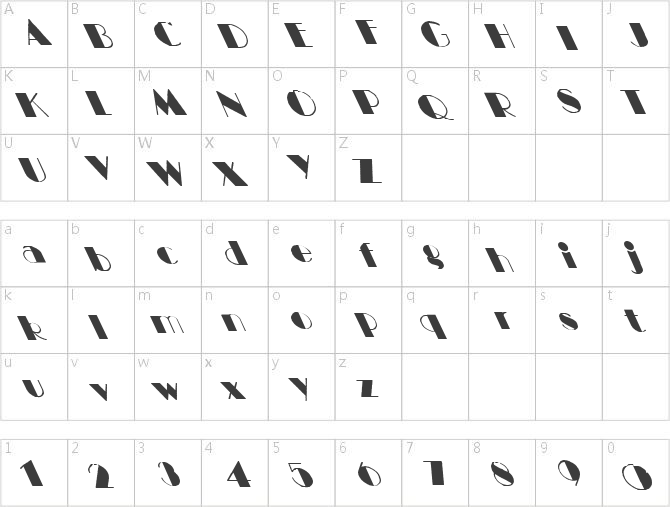
字体名称: BIGCITY
BIGCITY-Normal Extreme Lefty
BIGCITY-Normal Extreme Lefty字体字库是一款让人赏心悦目、百看不厌的英文字体,适合各类广告和产品包装设计应用,字体大小0.04MB,格式为ttf字体,上传用户是邹湾湾湾湾,作者/版权方为未知